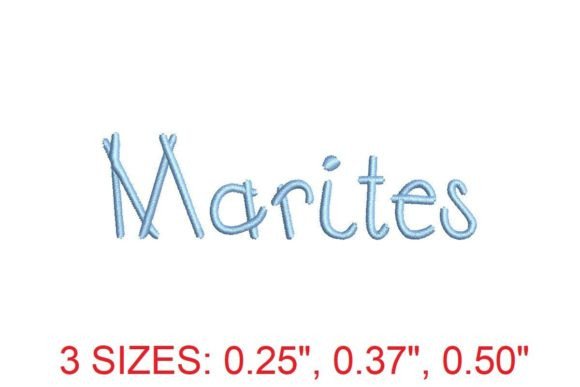
Marites Font
หากคุณกำลังมองหาเนื้อหาคุณภาพสูงเช่น Marites Font แพ็คเกจพรีเมียมนี้เป็นตัวเลือกที่ยอดเยี่ยมสำหรับโปรเจ็กต์สร้างสรรค์ของคุณ
สร้างขึ้นอย่างแม่นยำ Marites Font ให้เวกเตอร์ที่สะอาด พิมพ์ตัวอักษรที่ราบรื่น และใบอนุญาตเชิงพาณิชย์เพื่อความสบายใจ
ไม่ว่าคุณจะสร้างผลิตภัณฑ์ POD (Print on Demand) คำเชิญงานแต่งงาน หรือกราฟิกโซเชียลมีเดีย Marites Font ก็เหมาะสมอย่างยิ่ง